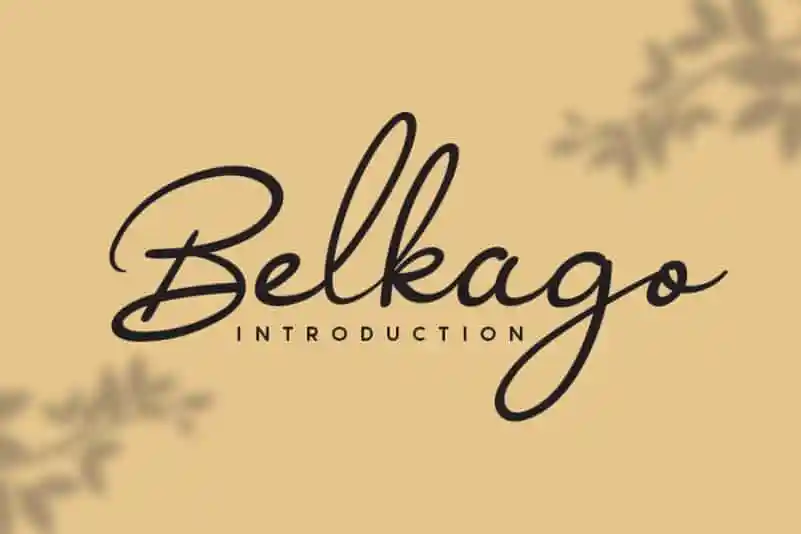
Belkago Handwritten Font – Download Grátis
A Belkago Handwritten Font é uma obra-prima do design que surgiu a partir de uma combinação única de um traço suave de caneta e um esboço delicado, resultando num estilo extremamente encantador e autêntico. Esta fonte escrita à mão, repleta de originalidade e exclusividade, é perfeita para iluminar qualquer projeto DIY. Suavemente realista e cheia de personalidade, ela traz uma delicadeza que torna o texto ainda mais emocional e envolvente, criando um toque único a cada letra. Seja em cartazes, logotipos ou até mesmo em mensagens pessoais, esta fonte escrita à mão faz com que qualquer trabalho seja encantador de uma maneira fascinante. Experimente Belkago Handwritten Font para trazer vida e personalidade a seus projetos!